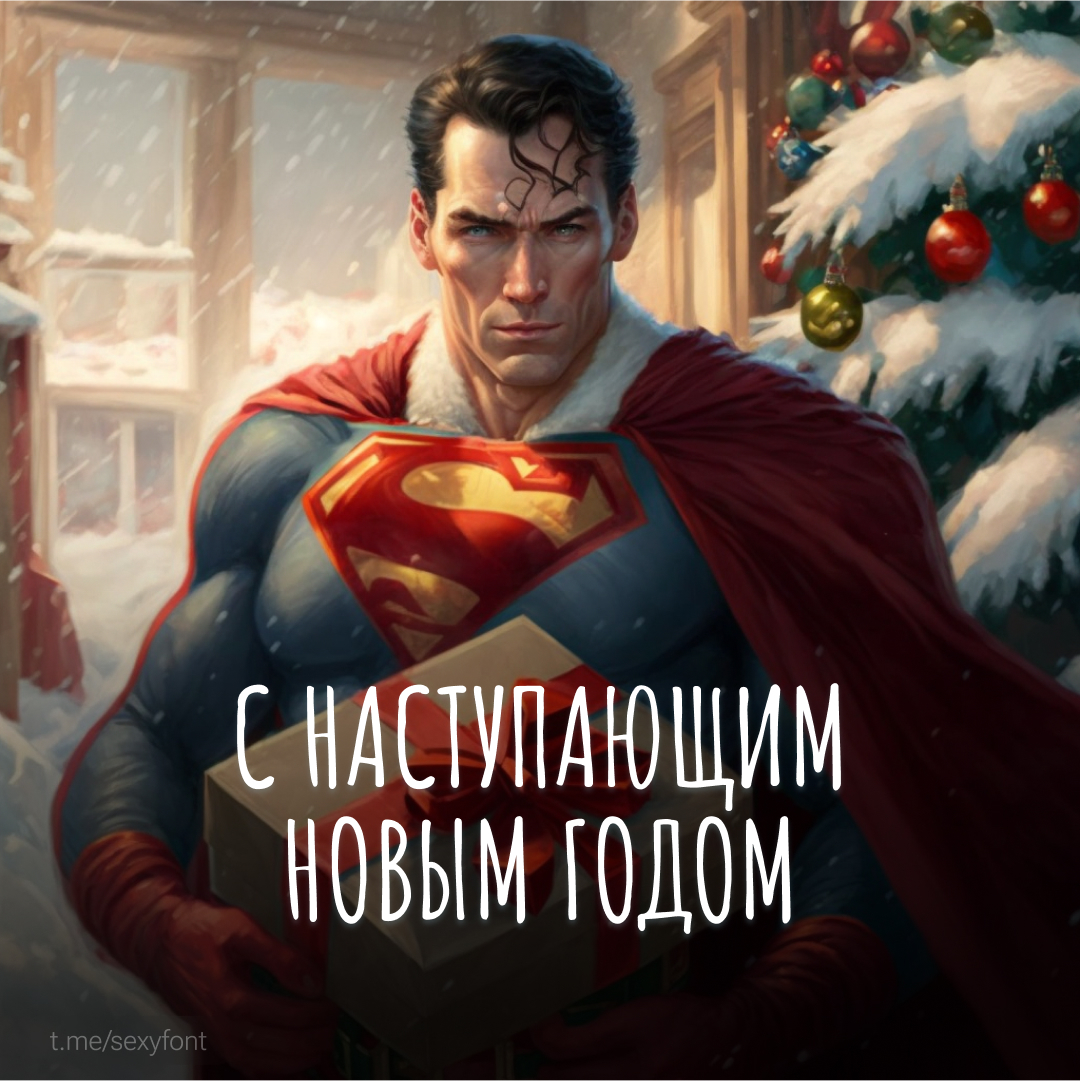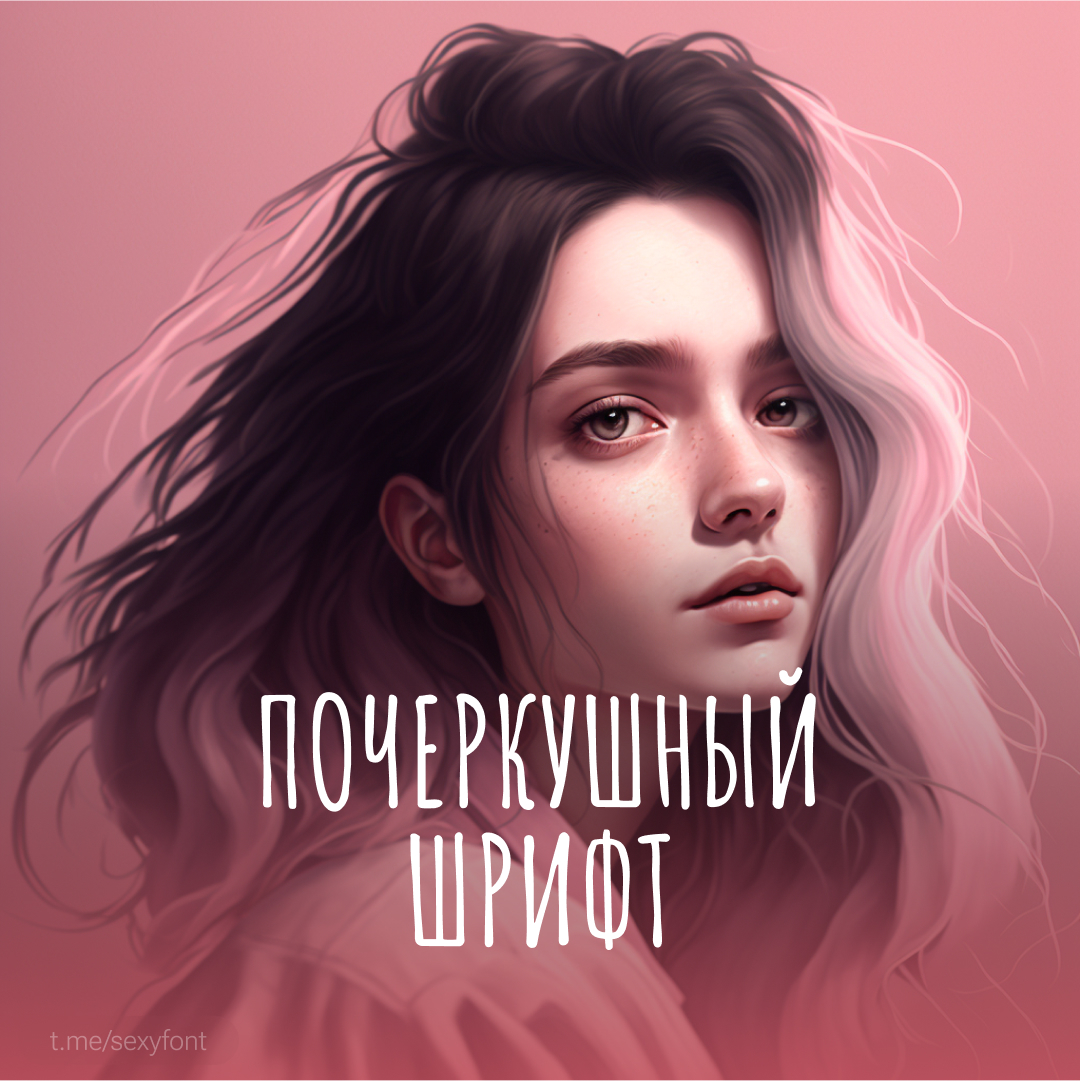
Аматик. Бесплатный кириллический шрифт
Аматик. Минималистичный шрифт для ваших работ. Описание будет такое же минималистичное) Автор: Vernon Adams. Презентация моя. Бесплатно для всего.